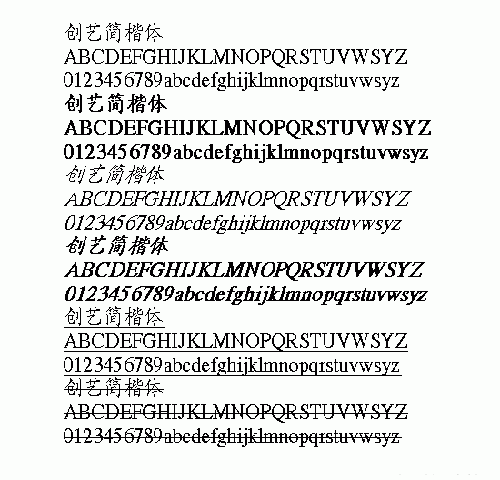
創(chuàng)藝簡(jiǎn)楷體字體是一個(gè)非常美觀的字體。具備了楷書(shū)字體所有特點(diǎn),同時(shí)又帶有藝術(shù)字體的特征。可以用來(lái)設(shè)計(jì)廣告等。兼容多種計(jì)算機(jī)操作系統(tǒng)!歡迎下載使用。
使用說(shuō)明楷書(shū)楷書(shū)也叫正楷、真書(shū)、正書(shū)。由隸書(shū)逐漸演變而來(lái),更趨簡(jiǎn)化,橫平豎直?!掇o?!方忉屨f(shuō)它“形體方正,筆畫(huà)平直,可作楷?!?。這種漢字字體端正,就是現(xiàn)代通行的漢字手寫正體字。